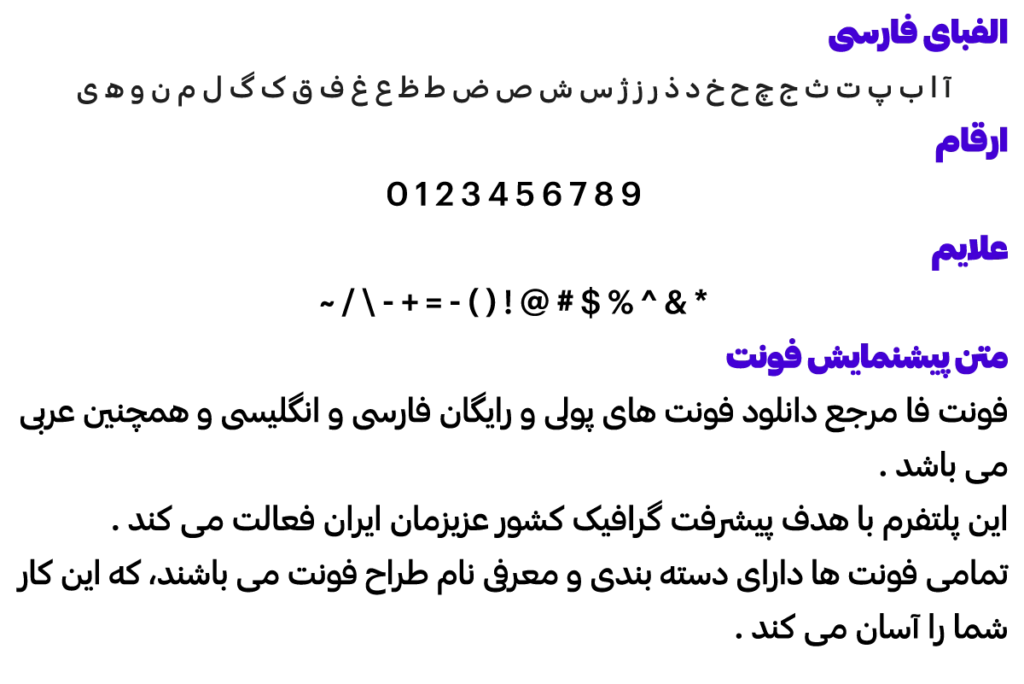
فونت فارسی گرافیک – Graphik
نوع فونت: فونت عنوان و فونت متن
توضیحات و معرفی فونت گرافیک
فونت فارسی/عربی گرافیک ( Graphik ) یکی از مجموعه فونت های آزاد می باشد، همچنین نوع فونت عنوان و متن می باشد.
این تایپ فیس در اصل یک فونت عربی است که با افزودن حروف فارسی، به فونتی مناسب برای نوشتار فارسی تبدیل شده است.
همچنین فونت در 8 وزن سنگین و پر رنگ و نیمه پر رنگ و فوق العاده پررنگ و سبک و متوسط و نازک و فوق سبک است.
در لیست زیر می توانید وزن های این فونت فوق العاده زیبا را ببینید.
- Graphik Black
- Graphik Bold
- Graphik DemiBold
- Graphik ExtraBold
- Graphik Light
- Graphik Medium
- Graphik Thin
- Graphik UltraLight
شعر زیبای وطنم که با این تایپ فیس نوشته شده است را تماشا کنید…